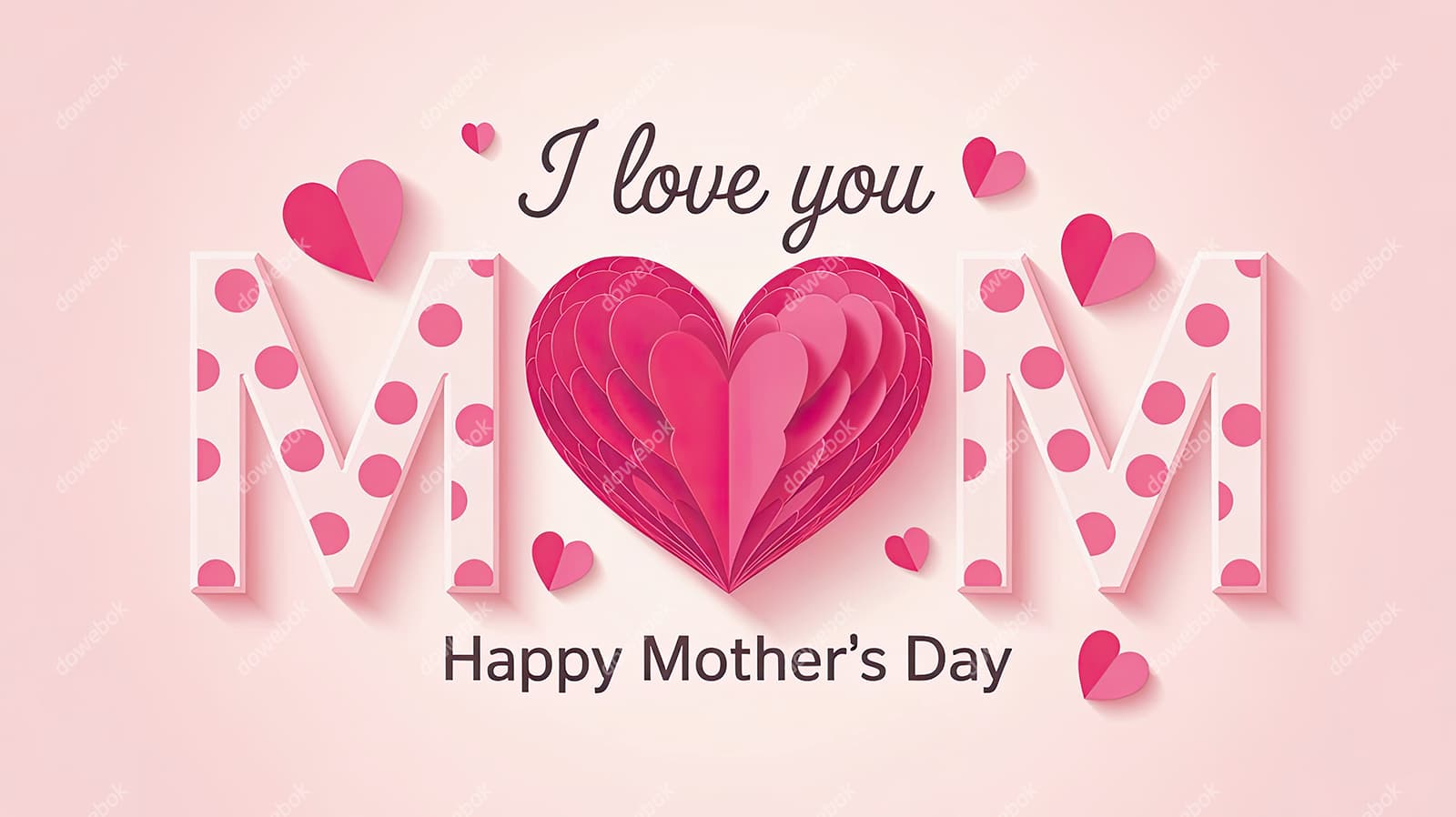
这是一款由 MOM 字母设计母亲节图片素材,画面中心是 “MOM” 字样,字母为白色底粉色圆点图案。中间是一个由多层粉色心形组成的立体爱心,极具层次感。上方有手写体 “I love you”,下方写着 “Happy Mother’s Day”。浅粉色背景上散落着小心形装饰,整体传递出对母亲的深情与节日祝福,氛围温暖甜蜜,充满爱意。